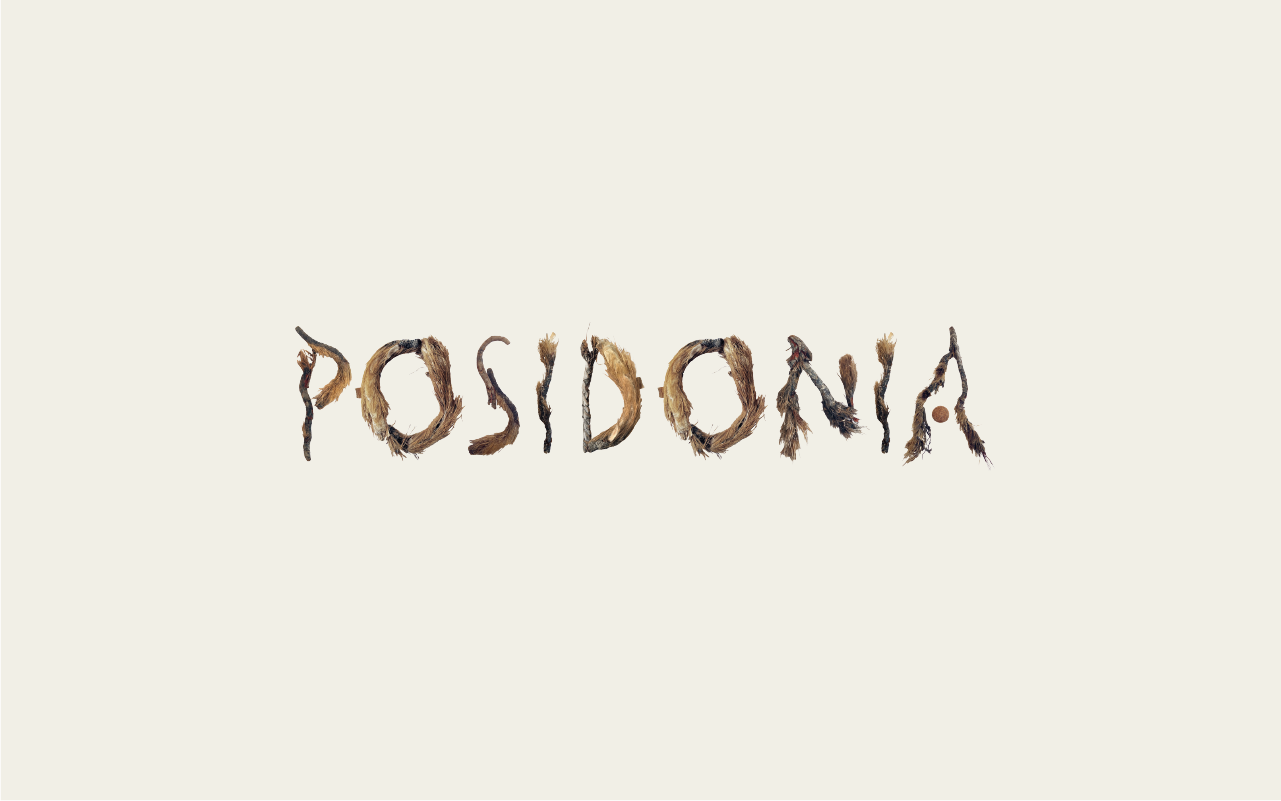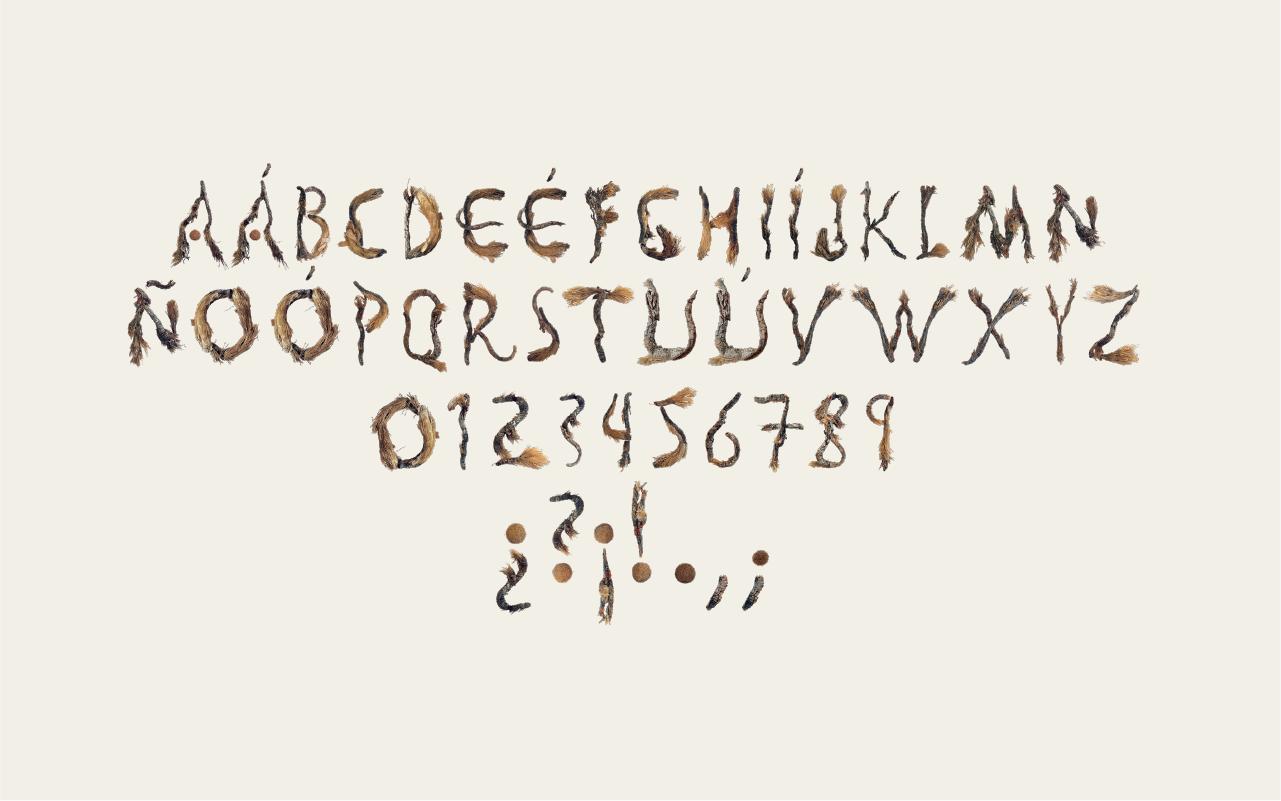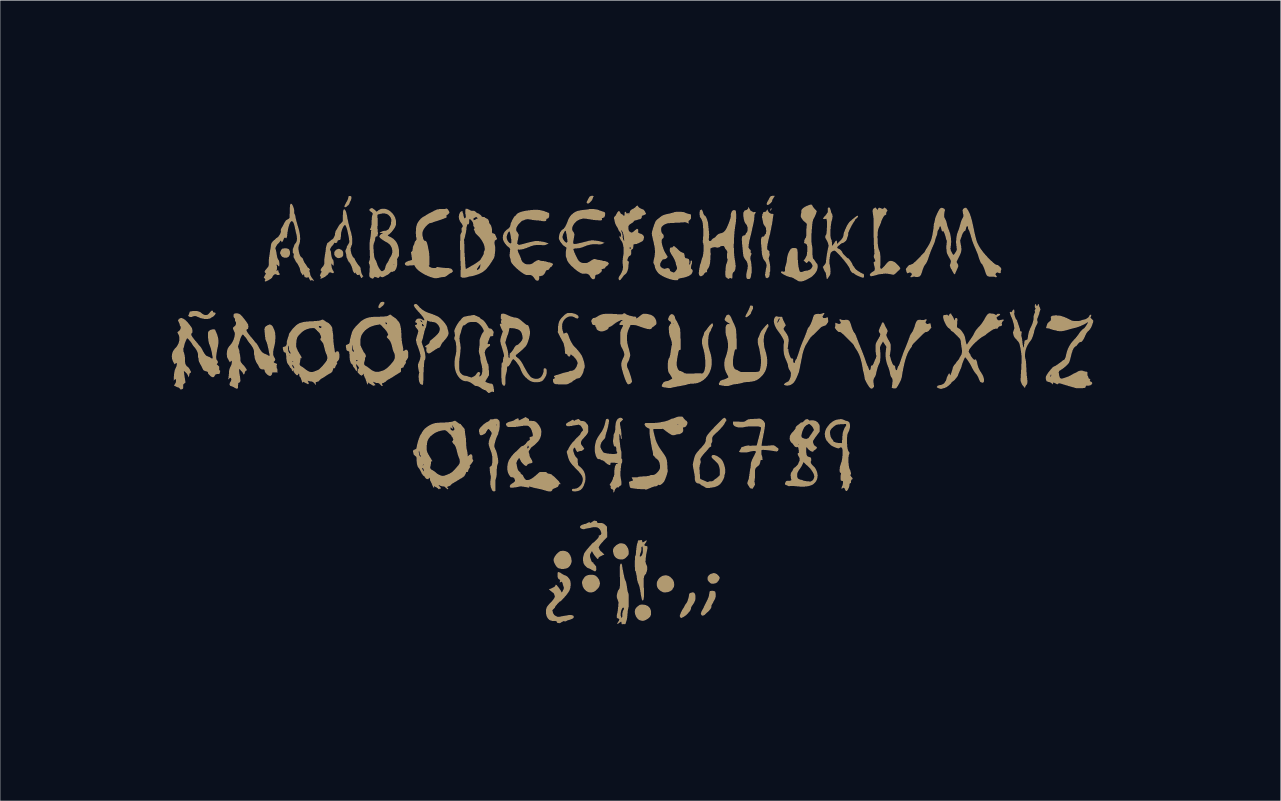
«Posidonia» es una nueva tipografía creada por los diseñadores Marina Zaragoza y Luis Zaragoza.
“Posidonia” es el nombre de una nueva pogra a inspirada en la posidonia oceánica, una planta acuá a esencial para la conservación del Mediterráneo. Marina Zaragoza y Luis Zaragoza fundadores del estudio de creatividad Posidonia Design que desde Alicante han diseñado este nuevo po de letra porque les importa la salud del Mediterráneo y quieren llamar la atención sobre el papel que juega esta increíble planta para la conservación y salud de este mar.
La protección de la Posidonia es indispensable para la conservación del Mediterráneo. Esta planta forma extensas praderas verdes que liberan oxígeno a la atmósfera, proporcionan refugio a numerosas especies marinas, consolidan los fondos y frenan la erosión de la costa y de las playas.
Posidonia Design ha diseñado esta tipografía recogiendo posidonia seca de las playas y costas y componiendo todas las letras y números con trozos de los tallos y de las hojas. El resultado ha sido la creación de la primera tipografía del mundo basada en esta planta endémica del Mediterráneo, de uso totalmente libre y gratuito.